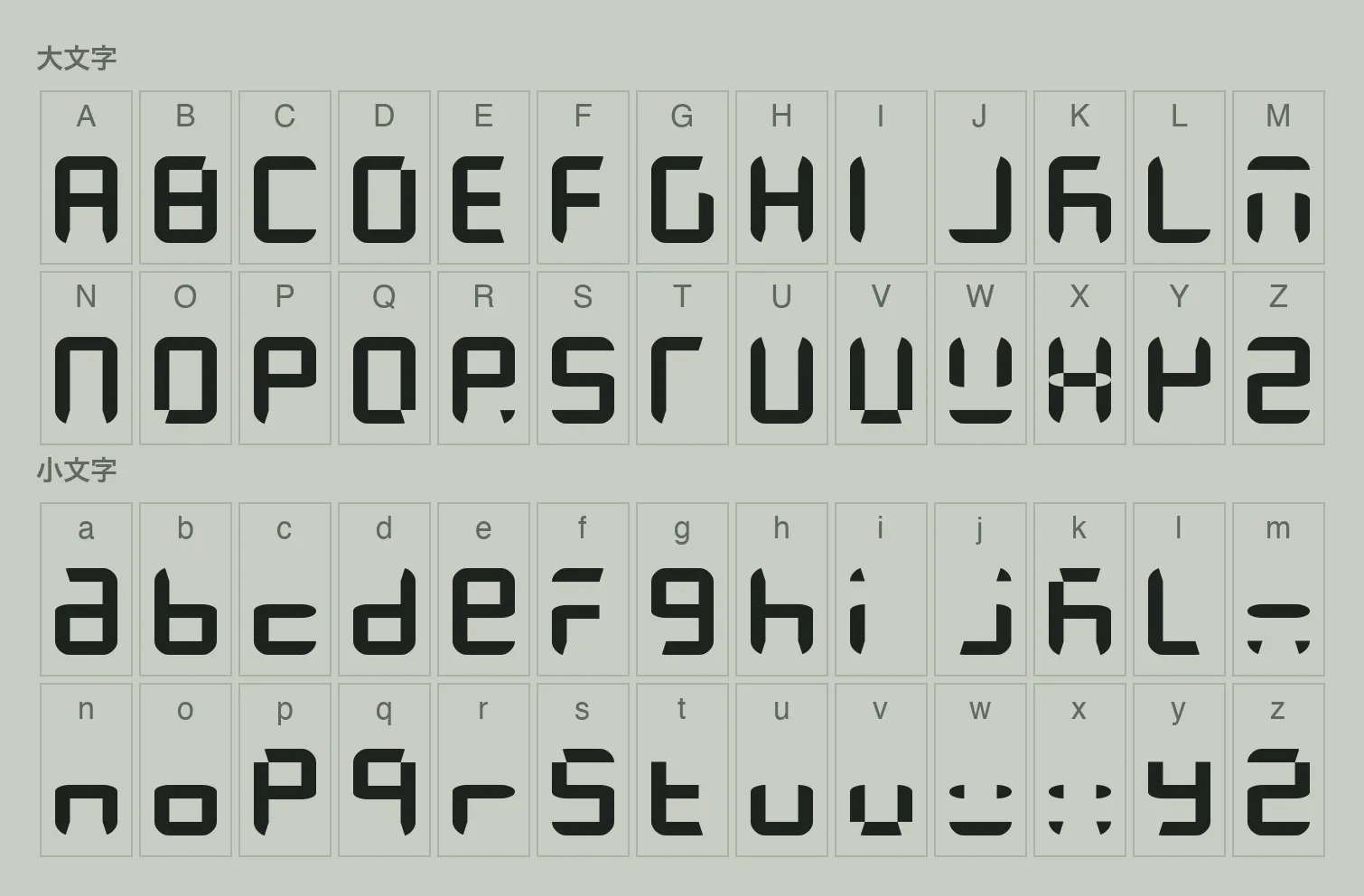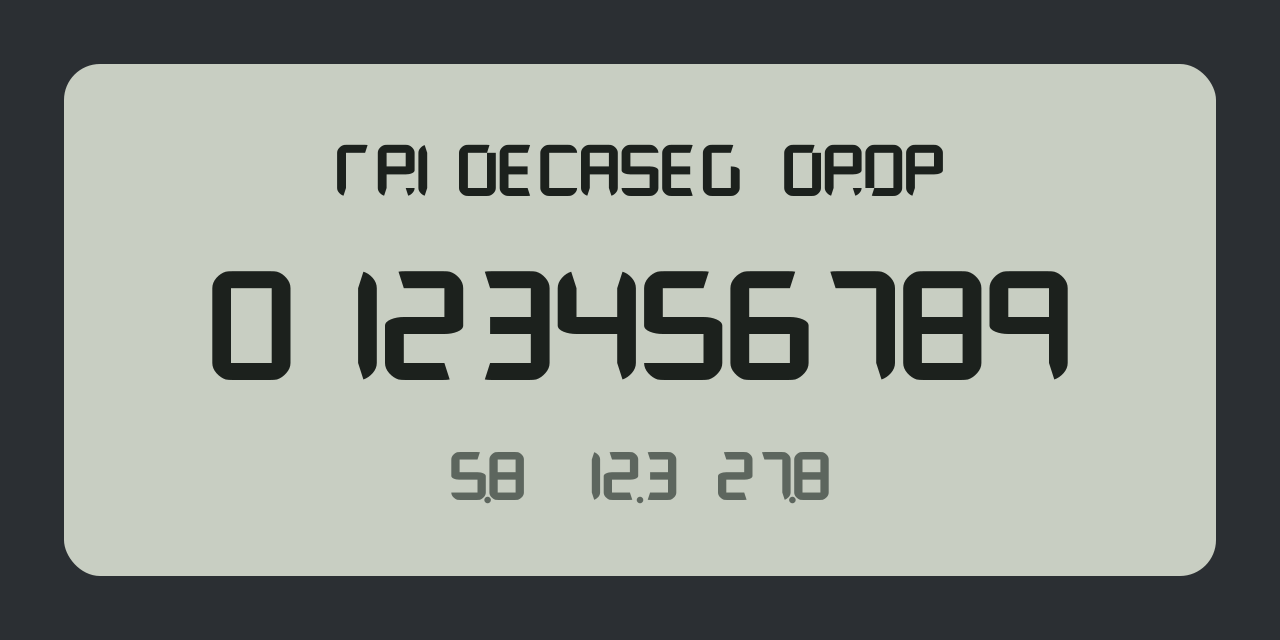
数字と小数点の見本です。画像ではなく Web フォントなので、文字を書き換えて試せます。
英字も収録しています。
• 数字 0〜9
• 英大文字 A〜Z、英小文字 a〜z(それぞれ別の字形)
• 記号 . - _ / [ ]、スペース
英字は13本のセグメントで表現しているため、形だけでは分かりにくい字もあります。対応は次のとおりです。
英字の字形は、ソケセテさんが X で公開している7セグメントの英数字も参考にしました。ラテン文字の大文字・小文字と算用数字が、互いに同じセグメントの形にならないように割り当てた字形です。
小数点 . は、数字や英字の後では、カーニングで直前の文字の右下に重なります。液晶と同じように、12.3 を3桁分の幅で表示できます。スペースの後や行頭の . は、空白の1桁の右下に表示します。
カーニングが効かない環境では、. がいつも1桁分の幅を使います。
FreeStyle Optium Neo は、アボット社の血糖・ケトン測定器です。血糖値と血中ケトンを測定でき、インスリンの投与量の記録もできます1。
測定値を表示する液晶の数字は、一般的な7セグメントとは違う、13本のセグメントを組み合わせた特徴的な形をしています。Tridecaseg Drop は、この文字をもとに作りました。名前の Tridecaseg は「13(trideca)のセグメント」、Drop は血液の一滴にちなんでいます。